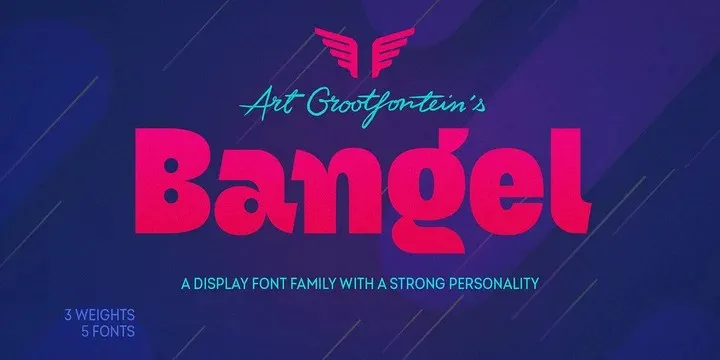
A Bangel Font é uma elegante fonte de display que oferece quatro estilos únicos e modernos, combinando elementos geométricos com uma expressividade lúdica e alegre. Esta fonte sans-serif abrange uma riqueza visual interessante e dinâmica, ideal para gráficos em destaque, anúncios de mídia social ou design gráfico onde você deseja dar um toque criativo ao seu projeto. Com seus traços modernos e geometricamente definidos, a Bangel Font captura a atenção do público com suas formas distintas e vibrantes, tornando-a uma escolha perfeita para qualquer visual que deseja estabelecer um padrão único. Com sua expressividade única, você poderá transmitir emoções através dos textos de forma elegante e moderna.